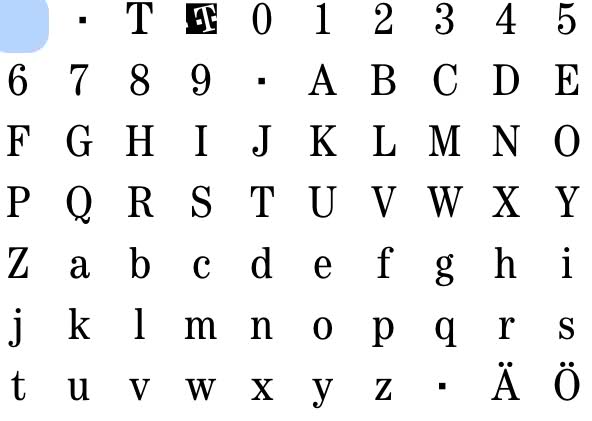
Schrift ähnliche TeleGrotesk (Telekom)
kennt jemand eine Schrift die ähnlich der TeleGrotesk ist? Man kann diese zwar kaufen aber vermutlich nicht in Bereichen einsetzen, die nichts mit der Telekom zu tun hat...
Die Tele Grotesk und die Tele Antiqua und die Tele Logo sind von
URW 1994/95 entwickelt für die Telekom. Siehe Bilder. Wegen einen Auftrag befinden die sich (schon lange) auf meinem Rechner. Die Tele Grotesk ist eine überarbeitete Helvetica und die Tele Antiqua kommt von der Century. Alles exclusiv fürs CD der Telekom. Die "Corporates" dürften die ersten jahren auch nur von Mercedes verwendet werden. So auch bei der Telekom. Das ist aber inzwischen nicht mehr so (glaube ich...)
Eine ähnlichere wie die Helvetica wirds offiziell nicht geben, vielleicht bei den Freien (clones). Das kleine a wurde von der leichte an bis zur ultra nur fetter gemacht und bekam nicht wie bei der Helvetica halbfett und fett eine andere Form.
aber aber liebe kollegen, schon mal was von der akzidenz grotesk gehört oder gesehen, castle type hat diese geclont und bei fontshop untergebracht....??!!!
Peinlich. Die Standard ist ein klein bisschen gestaucht gegenüber der AG und ein paar Buchstaben (s,S,Q) sind abgeändert. Wegen dem Stauchen ist mir das wohl nicht aufgefallen. :oops:
ich fand noch den "nobel" als look-a-like.